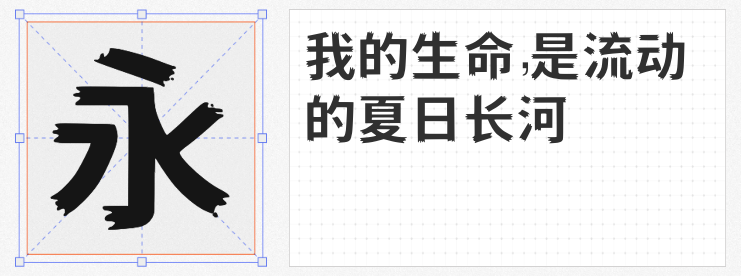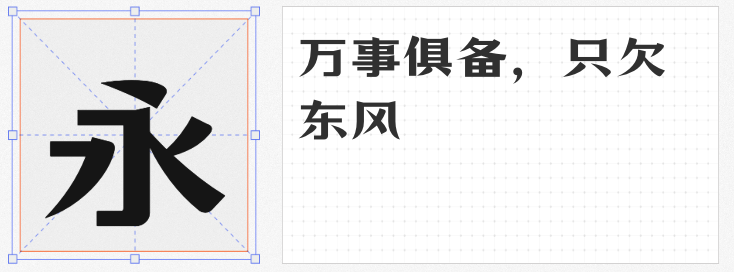
在商业设计领域,字体不仅是信息传递的载体,更是塑造品牌调性的关键元素。然而,预算限制常让设计师在创意与成本间陷入两难。以下四款免费商用字体,以独特的创意风格和广泛的适用性,为项目提供高性价比的解决方案,助力设计突破常规,展现专业质感。
这款标题黑体将中国古建筑的“飞檐”元素融入笔画设计,末端尖角外挑如屋檐舒展,非正圆倒角的结构转角则赋予字体人文温度。在保留黑体简洁基因的同时,通过细节处的复古巧思,让标题文字既具现代几何感,又暗藏东方美学意蕴。适用于文化类、国潮风格的设计场景,轻松传递历史底蕴与时尚态度。
以黑体为基底,鼎猎刺猬体通过锯齿状边缘的撕裂感,打造出“魔丸哪吒”般的叛逆气质——外露锋芒下包裹着柔软内核。这种矛盾美学使其成为美食餐饮、潮流展会、美妆护肤等行业的理想选择:既能用锐利笔触吸引眼球,又能以内在的稳健感传递品牌温度,让视觉表达更具层次与记忆点。
这款字体以粗壮笔画构建强烈视觉冲击力,却通过圆润的收笔处理消解了传统古风的厚重感,呈现出“刚中带柔”的独特气质。无论是餐饮品牌LOGO、文化海报还是包装设计,其古朴韵味与现代时尚的融合都能快速营造场景氛围,让设计在传递历史感的同时不失亲和力。
作为全兴酒业定制字体,万事全兴体脱胎于古典宋体的优雅骨架,却融入黑体的疏朗布局,形成“浑厚庄重而不失活力”的视觉语言。笔画转折处的克制处理,让文字在正式场景中彰显专业度,在年轻化设计中亦能传递个性态度,堪称品牌升级的“万能钥匙”。
这四款免费商用字体,以文化符号的解构、矛盾美学的碰撞、传统与现代的对话,为设计师提供了零成本的创意工具箱。无论是追求东方意境、叛逆态度还是历史厚重感,它们都能以专业级表现力,让设计在控制成本的同时,依然保持独特与高级。